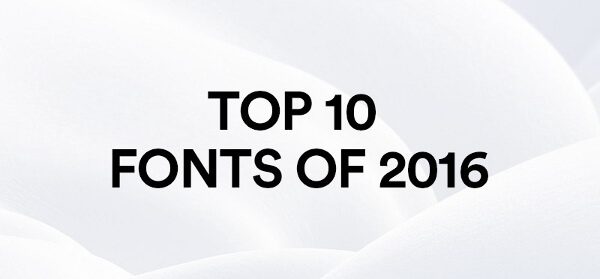
【circular】Webデザイナーがこぞって活用!欧文フォントTOP10
Maison
Maison Neue はTimo Gaessner氏によりデザインされ、2012年にリリースされたグロテスク・サンセリフ書体となります。
Maisonをリニューアルしたもので、最新のディスプレイでも映えるデザインと、再現技術を用いたフォントとなります。
Montserrat
Montserratは、アルゼンチンのデザイナーJulieta Ulanovsky氏によるジオメトリック・サンセリフ書体です。
ブエノスアイレスの近所にある看板からインスパイアを受けたそうです。
Apercu
Apercuは2010年にColophonからリリースされたグロテスク・サンセリフ書体です。
ColophonはイギリスのスタジオThe Ententeにより設立されたフォントメーカーです。
Circular
Circularはジオメトリック・サンセリフ書体で、スイスのデザイナーLaurenz Brunner氏によってデザインされました。
2013年にLinetoからリリースされ、CircularはAkkuratに引き続き、Brunner氏の2作目のフォントとなります。
Neuzeit
Neuzeit はジオメトリック・サンセリフ書体で、ドイツのデザイナーWilhelm Pischner氏によってデザインされました。
このフォントの起源は1928年にまでさかのぼり、時代を超えて愛されるフォントを目指してリリースされました。
Franklin Gothic
Franklin Gothicは1902年アメリカのデザイナーMorris Fuller Benton氏によりデザインされました。
書体はグロテスク・サンセリフです。
Supria Sans
Supria SansはHannes von Dohren氏によりデザインされ、2011年にHVD Fontからリリースされました。
書体はグロテスク・サンセリフとなります。こちらの書体は、Dohren氏の他のフォントと比べるとあまり使用されていないようですが、とても汎用性のあるフォントだと思います。
Pangram Sans
Pangram SansにはExtraLightからBlackまで7種類のフォントがそろっています。
ジオメトリック書体にインスパイアされたそうで、Webデザインの良さをさりげなく引き立ててくれるフォントです。
Museo Sans
Museo Sans はジオメトリック・サンセリフがどんな形式にも美しくフィットするように考えられて作られたデザインです。
Museoフォントをベースにデザインされ、モダンで洗練されたデザインが特徴です。
小さいサイズの文字も綺麗で、Webサイトやアプリケーションにも適しています。
Folio
FolioはKonrad Bauer氏とWalter Baum氏の共同でデザインされたネオ・グロテスク・サンセリフ書体です。
HelveticaとUniverseがリリースされたのと同じ年、1957年にリリースされました。